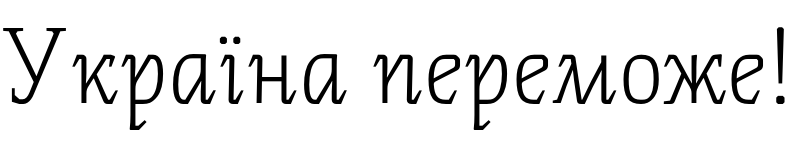
Асоціації зі шрифтом Thalweg Poetica Cond Ultra LightОсобистість і характер шрифта:
тонкий, легкий, освічений, стійкий, серйозний, розумний, худий, ритмічний, динамічний, різкий, чіткий, характерний, оригінальний, самобутній, сухий, осінній, гострий, колючий, незвичайний, дивний, дротяний, ламаний, експериментальний, макабричний, декоративний, кріповий, колоритний, творчий, чаклунський, магічний, химерний, ремісничий, складний, загадковий, історичний, ролевий, середньовічний, старовинний, казковий, артистичний, цікавий